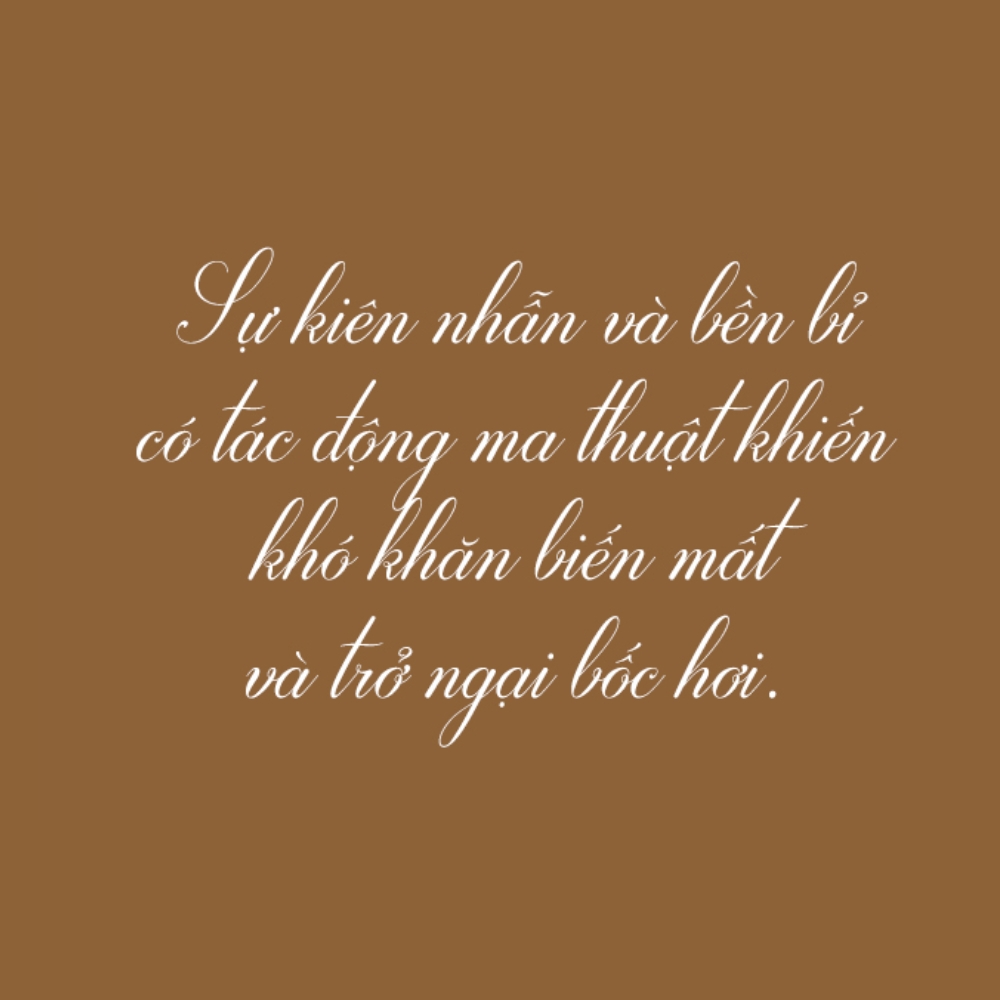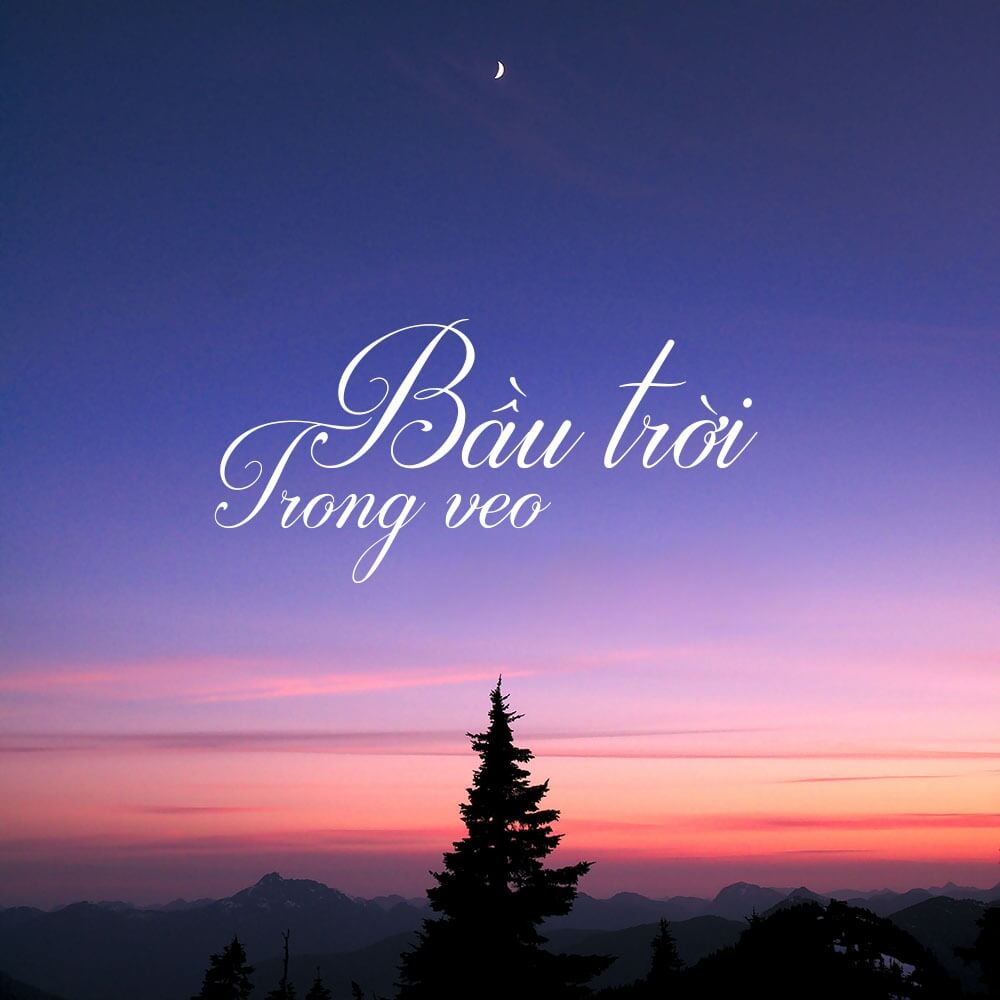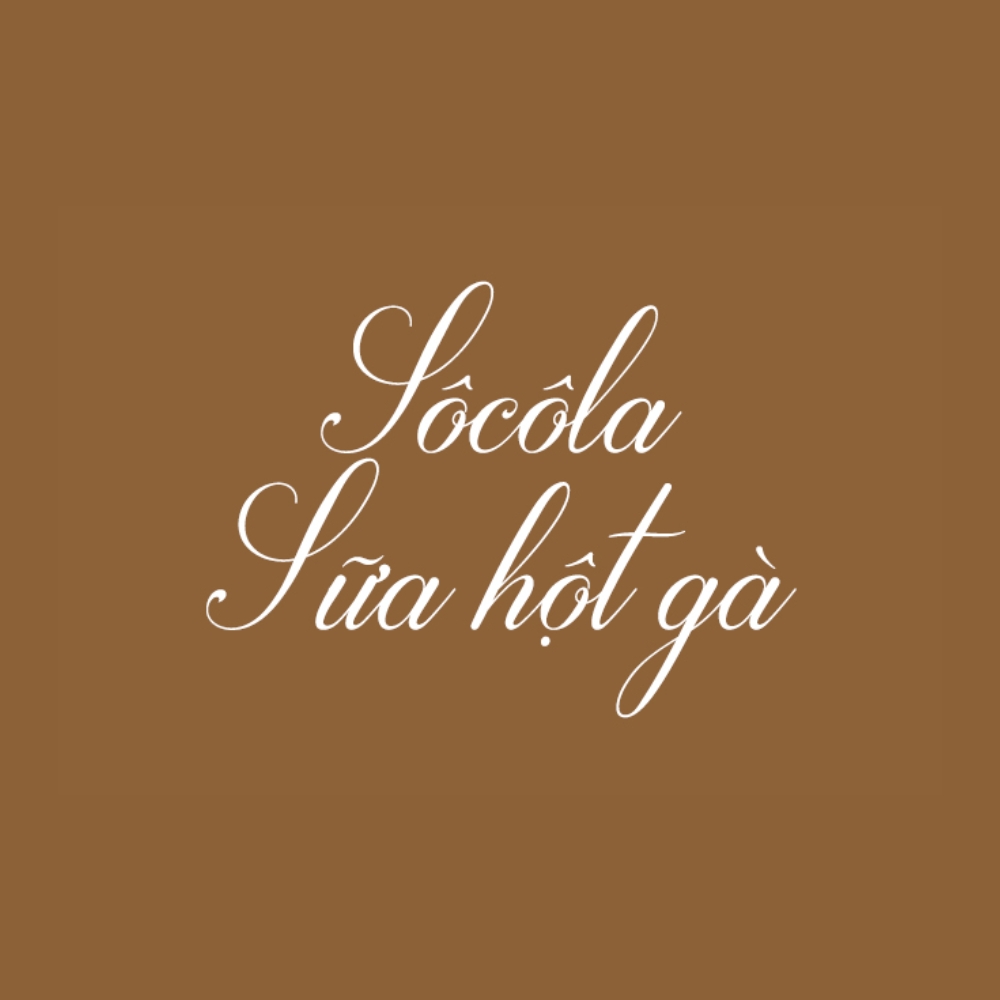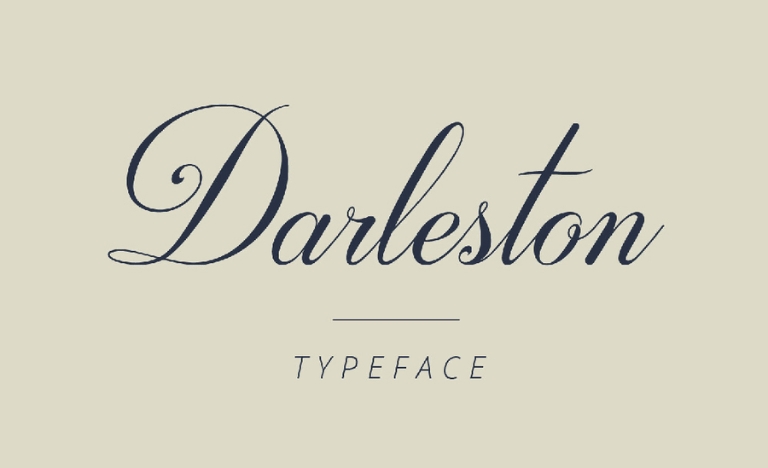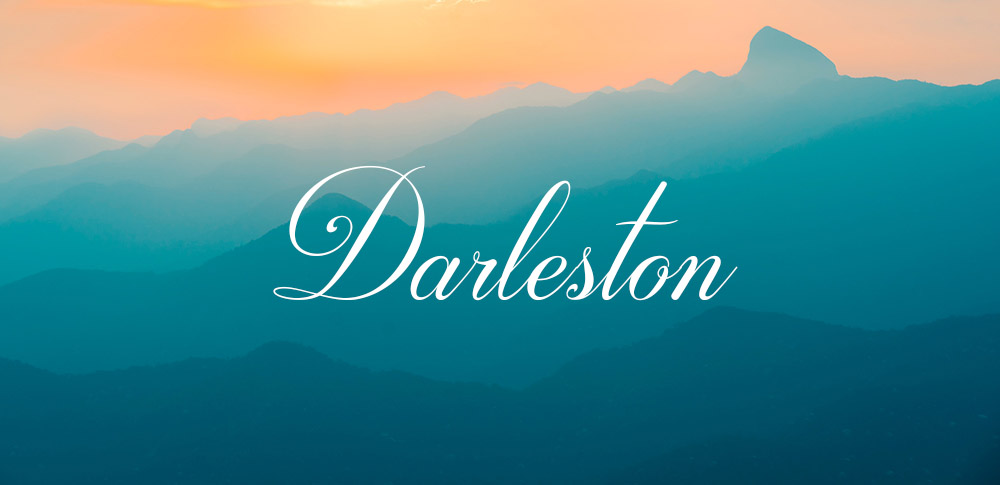
Darleston là một bộ font chữ thuộc dòng Script mang phong cách Calligraphy hiện đại, nổi bật với những đường nét uốn lượn bay bổng và đầy sự lãng mạn. Sự xuất hiện của font Việt hóa SVN Darleston mang lại một công cụ trình bày văn bản đầy tính nghệ thuật cho người làm sáng tạo, giúp các thiết kế tiếng Việt giữ được vẻ thanh lịch mà không gặp tình trạng lỗi dấu.
Đặc điểm nghệ thuật của font Việt hóa SVN Darleston
Điểm thu hút của SVN Darleston nằm ở nhịp điệu của các nét thanh và nét đậm đan xen nhịp nhàng, mô phỏng sinh động kỹ thuật viết tay thủ công cao cấp. Khác với các dòng font script thông thường, font Việt hóa SVN Darleston sở hữu cấu trúc chữ có độ nghiêng vừa phải, tạo cảm giác chuyển động mượt mà và tinh tế. Việc xử lý bộ dấu tiếng Việt được thực hiện kỹ lưỡng, giúp các dấu thanh phối hợp hài hòa với độ cao ký tự, duy trì tính thẩm mỹ xuyên suốt của bộ chữ gốc.
Sự tinh tế của bộ font này còn thể hiện qua hệ thống các nét nối tự nhiên giữa các chữ cái. Đặc điểm này giúp văn bản sau khi trình bày mang lại cảm giác chỉn chu và sang trọng, phù hợp để tạo điểm nhấn cho những không gian yêu cầu tính thẩm mỹ cao. Đây là phương án phù hợp để truyền tải những thông điệp mang tính cảm xúc, sự tận tâm và phong cách sống thượng lưu trong từng sản phẩm thiết kế.
| Phân loại phong cách | Modern Script / Calligraphy |
| Đặc tính hiển thị | Nét thanh đậm rõ rệt, uốn lượn mềm mại |
| Mục đích phù hợp | Logo, thiệp mời, tiêu đề sang trọng |
Gợi ý phối hợp: SVN Darleston có tính trang trí rất cao và nét chữ bay bổng. Để tổng thể thiết kế hài hòa, bạn nên kết hợp font này cùng một kiểu chữ Sans-serif mảnh và tối giản cho phần nội dung chi tiết, giúp bản thiết kế đạt được sự cân bằng thị giác ổn định.
03 Ứng dụng font SVN Darleston vào không gian sống
Nhờ vẻ ngoài sang trọng và giàu tính nghệ thuật, bộ font chữ này mang lại giá trị thẩm mỹ cao khi được ứng dụng vào các hạng mục trang trí và quảng bá công trình:
- Bảng tên cho Homestay và Resort cao cấp: Những nét uốn lượn của font svn-darleston Việt hóa rất ăn ý khi xuất hiện trên chất liệu mica gương, đồng hoặc gỗ sơn mài. Đối với các dự án nhà lắp ghép nghỉ dưỡng, font chữ này giúp nâng cao vị thế và tạo ấn tượng về sự tinh tế đối với du khách.
- Thiết kế Menu và Voucher dịch vụ: Sử dụng font này cho tiêu đề các hạng mục dịch vụ giúp thể hiện tư duy thẩm mỹ và sự chuyên nghiệp của đơn vị vận hành, giúp khách hàng dễ dàng cảm nhận được chất lượng không gian nghỉ dưỡng.
- Trang trí nội thất nghệ thuật: Bạn có thể dùng font Darleston để làm decal dán tường hoặc cắt chữ nổi trang trí tại khu vực sảnh chờ, phòng ngủ nhà lắp ghép nhằm tạo điểm nhấn mềm mại cho không gian sống hiện đại.
03 Lưu ý khi sử dụng font SVN-Darleston Việt hóa trong thiết kế
Để khai thác hiệu quả vẻ đẹp của dòng font Script thanh lịch này mà không làm rối mắt người xem, người thiết kế nên lưu tâm một số kinh nghiệm sau:
- Hạn chế sử dụng toàn bộ chữ in hoa: Đặc trưng của font Darleston là nét nối mượt mà giữa các chữ thường. Việc sử dụng toàn bộ chữ in hoa sẽ làm mất đi nhịp điệu tự nhiên và gây khó khăn cho việc nhận diện mặt chữ.
- Nới rộng khoảng cách dòng: Do các nét uốn lượn của font có xu hướng vươn rộng, bạn cần để khoảng cách dòng thoáng một chút để các ký tự không bị chồng chéo, giữ được sự minh bạch cho văn bản.
- Lựa chọn kích thước hiển thị phù hợp: Với các nét thanh mảnh, font chữ này phát huy hiệu quả thị giác cao khi được trình bày ở kích thước trung bình đến lớn trên nền màu có độ tương phản rõ rệt.